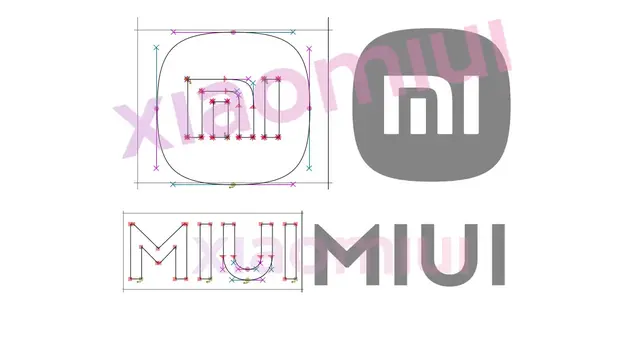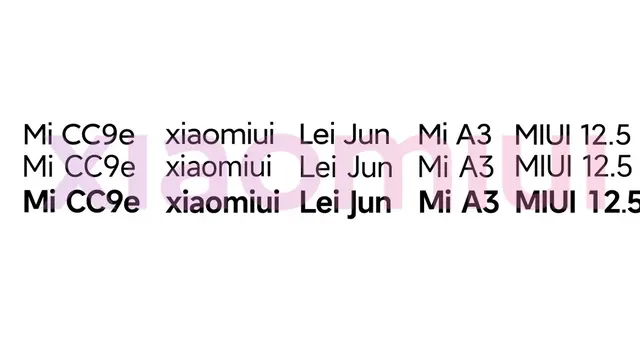
Liputan6.com, Jakarta - Xiaomi terus memperbarui sistem operasi MIUI untuk smartphone-nya secara berkala. Kini Xiaomi bahkan bersiap untuk meluncurkan MIUI 13Â yang berbasis Android 12, pada akhir bulan ini.
MIUI terbaru diharapkan untuk resmi meluncur pada 28 Desember 2021. Namun, belum dirilis, sejumlah aspek sudah bocor, termasuk font atau jenis tulisan baru Mi Sans yang bakal dipakai Xiaomi untuk MIUI 13.
Mengutip Gizmochina, Senin (20/12/2021), bocoran baru memperlihatkan tampilan Mi Sans serta font Mi Prototype 210317 yang digunakan dalam sistem operasi MIUI 13 mendatang.
Font baru ini akan menggantikan font Mi Lan Pro VF (Little Milan Pavilion Pro VF) yang digunakan saat ini oleh Xiaomi.
Dari bocoran tersebut, terlihat bahwa font baru memiliki teks yang lebih membulat dengan garis yang lebih halus dibandingkan font saat ini. Dengan begitu, font yang akan dipakai pada MIUI 13 terlihat lebih modern.
Selain itu, terungkap pula bahwa font tersebut berisi dua karakter khusus yakni logo Xiaomi dan logo MIUI
Berbeda dengan Font di MIUI Saat Ini
Masih berdasarkan bocoran ini pula, font Mi Sans baru yang akan dipakai Xiaomi pada MIUI 13 berbeda dari font yang tersedia di versi saat ini. Font Mi Lan Pro VF telah dipakai oleh Xiaomi sejak di MIUI 11.
Dengan MIUI 12.5, perusahaan mengganti nama font yang sama menjadi Mi Sans untuk mempersiapkan pertumbuhan besar yang akan datang.
Sejauh ini tidak banyak yang diketahui secara spesifik apa saja yang ditingkatkan perusahaan dengan MIUI terbarunya.
Namun kemungkinan bakal ada perubahan besar dalam hal desain (termasuk dengan kehadiran font baru) dan penambahan sejumlah fitur baru.
Perubahan di Desain Tulisan